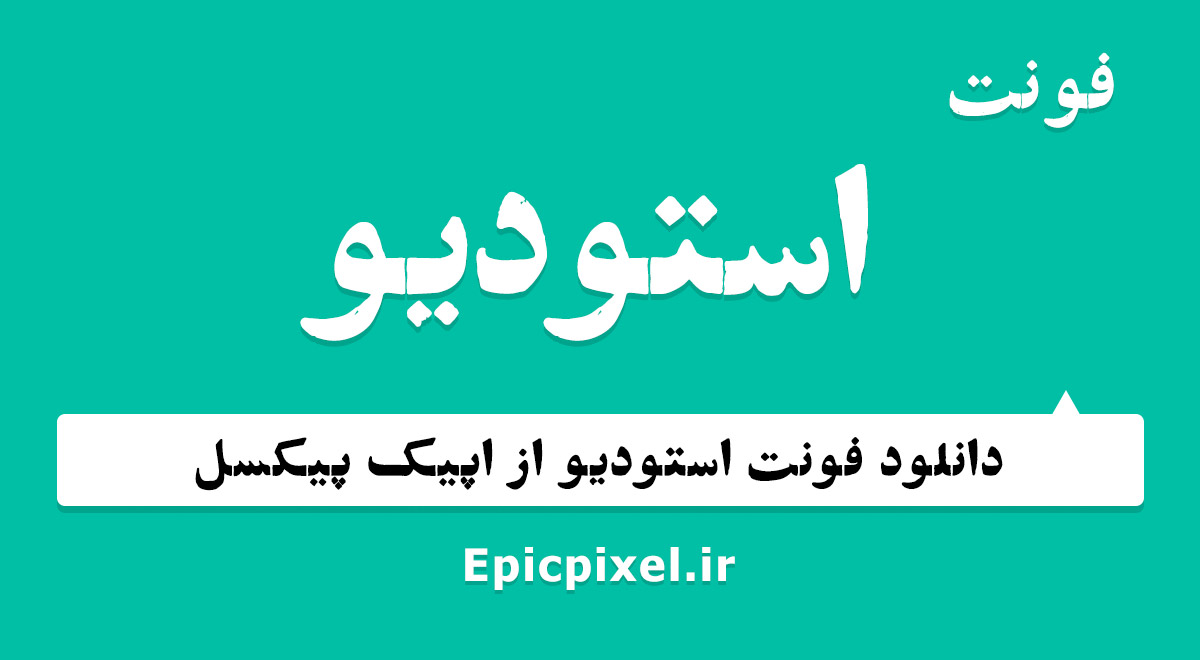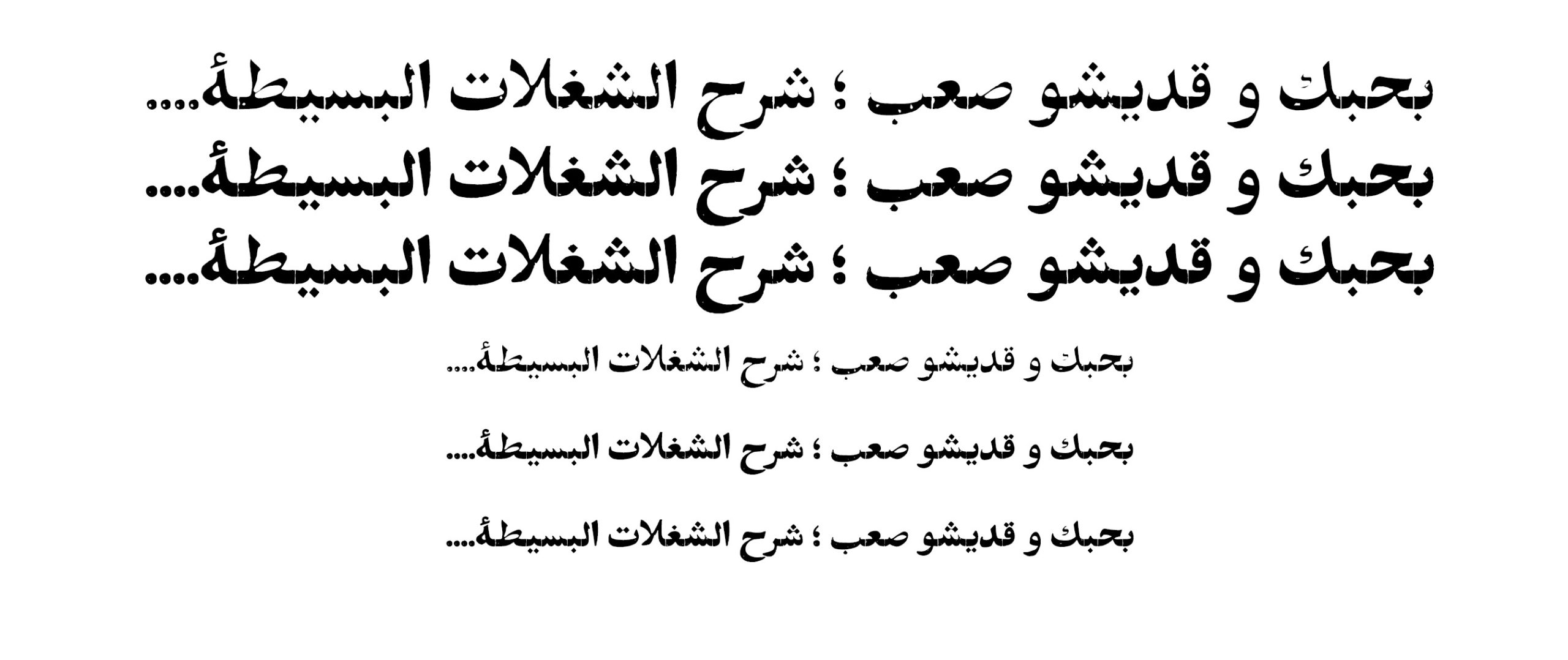
| ⭐ توضیحات | مجموعه ای کامل از فونت های استدیو و نسخه شبیه سازی شده اپیک استودیو
فونت اپیک استدیو با پشتیبانی از حروف فارسی ، انگلیسی / لاتین ، اعداد فارسی Fu Num شامل نسخه وب |
اصلا شبیه نمونه نیست
اوایل انقلاب از این فونت خیلی استفاده می شد
حتی میشه گفت فونت تیتر و عنوان جایگزین های این فونت هستند